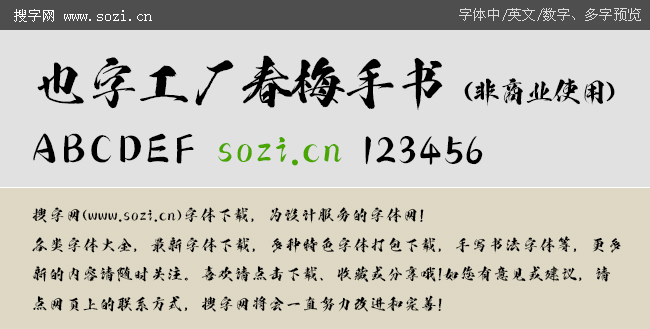
也字工厂春梅手书
搜字网给大家提供一款也字工厂春梅手书(非商业使用)中文字体下载,也字工厂春梅手书是一款书法字体,字体书写流畅,结构简洁大方,是一款视觉效果非常不错的手写毛笔书法字体。适合应用于海报设计、包装设计、网页设计等应用(此字体为个人非商用版,商用可以联系:官方网址:https://yefont.com/home,联系方式:13798980448)。